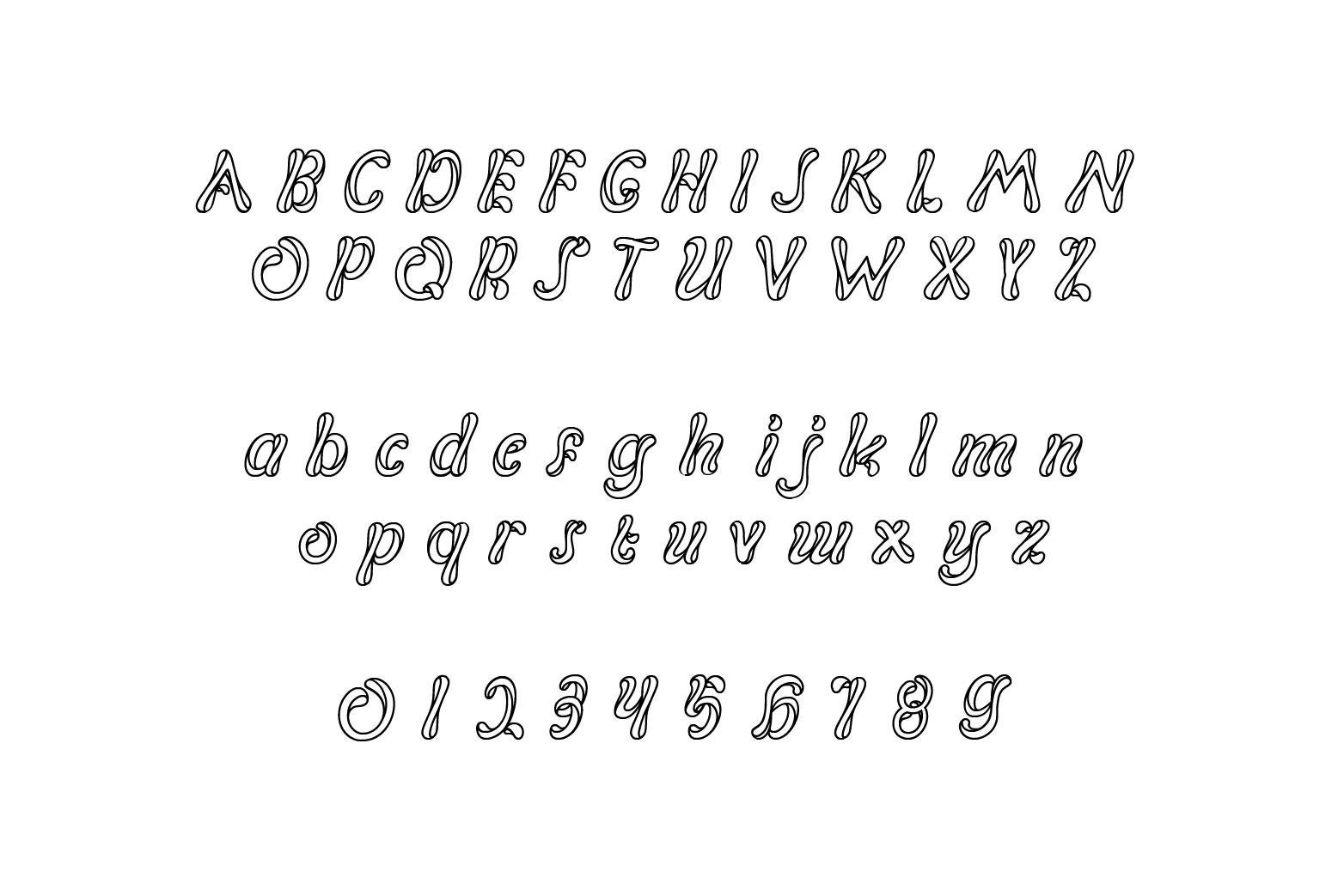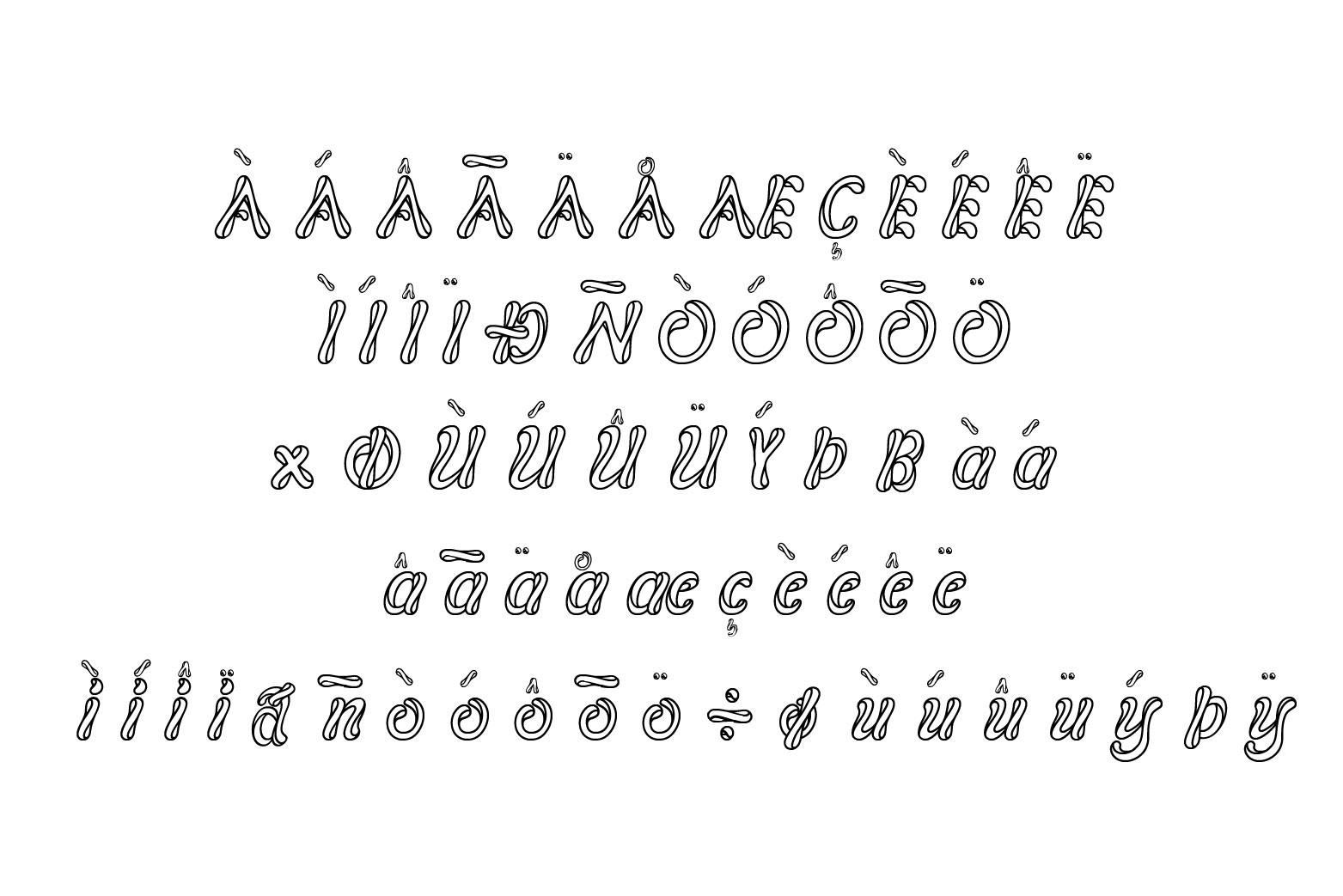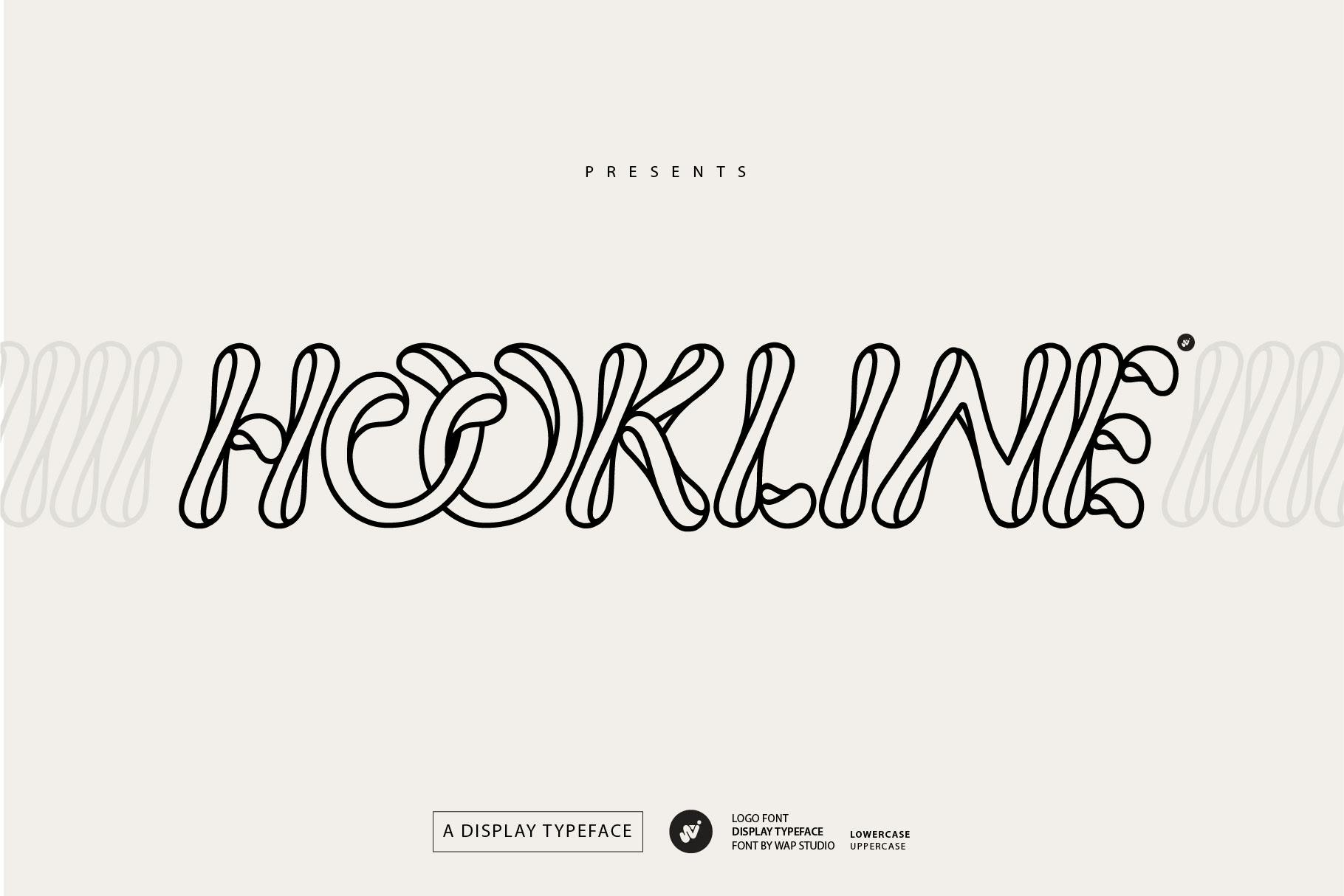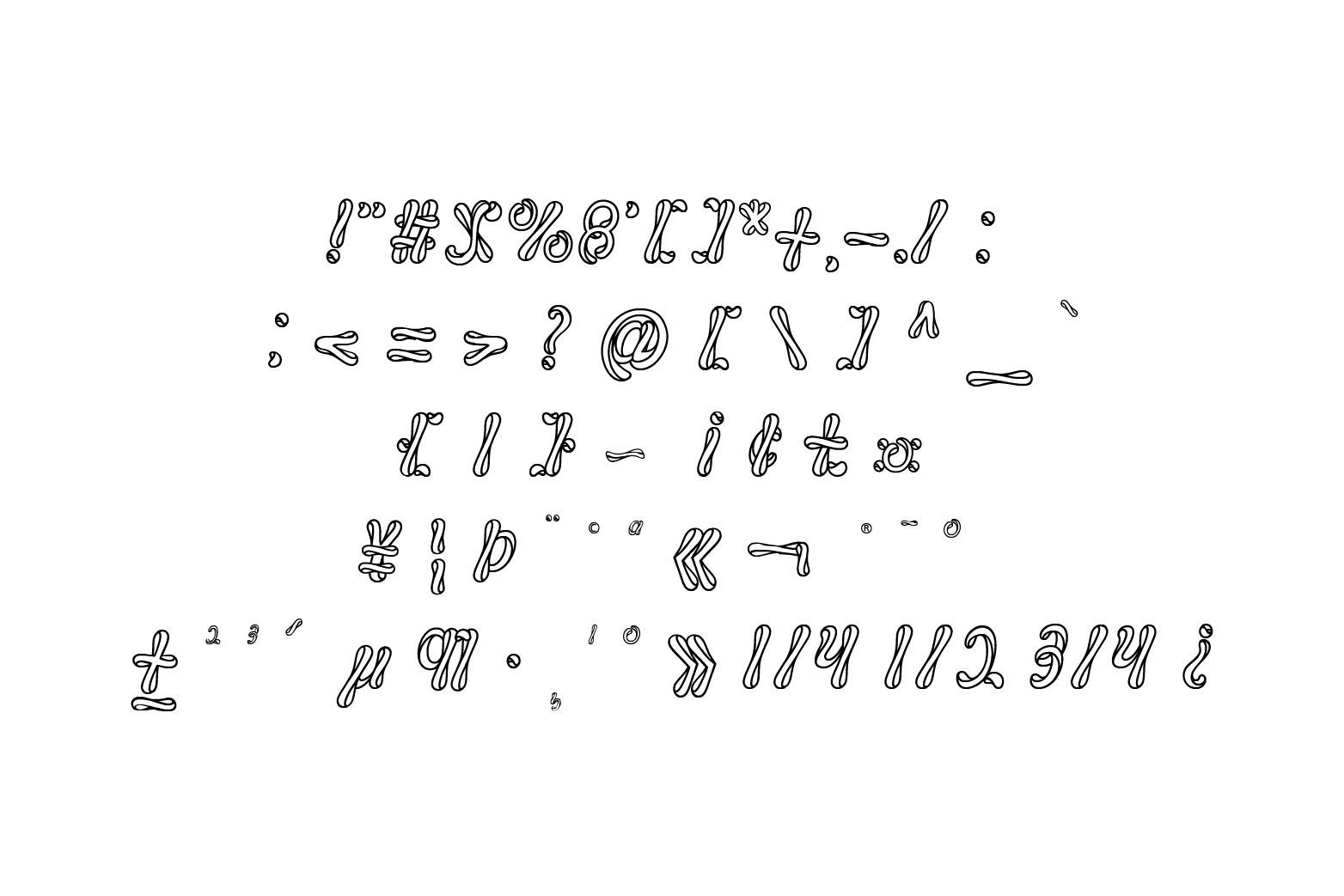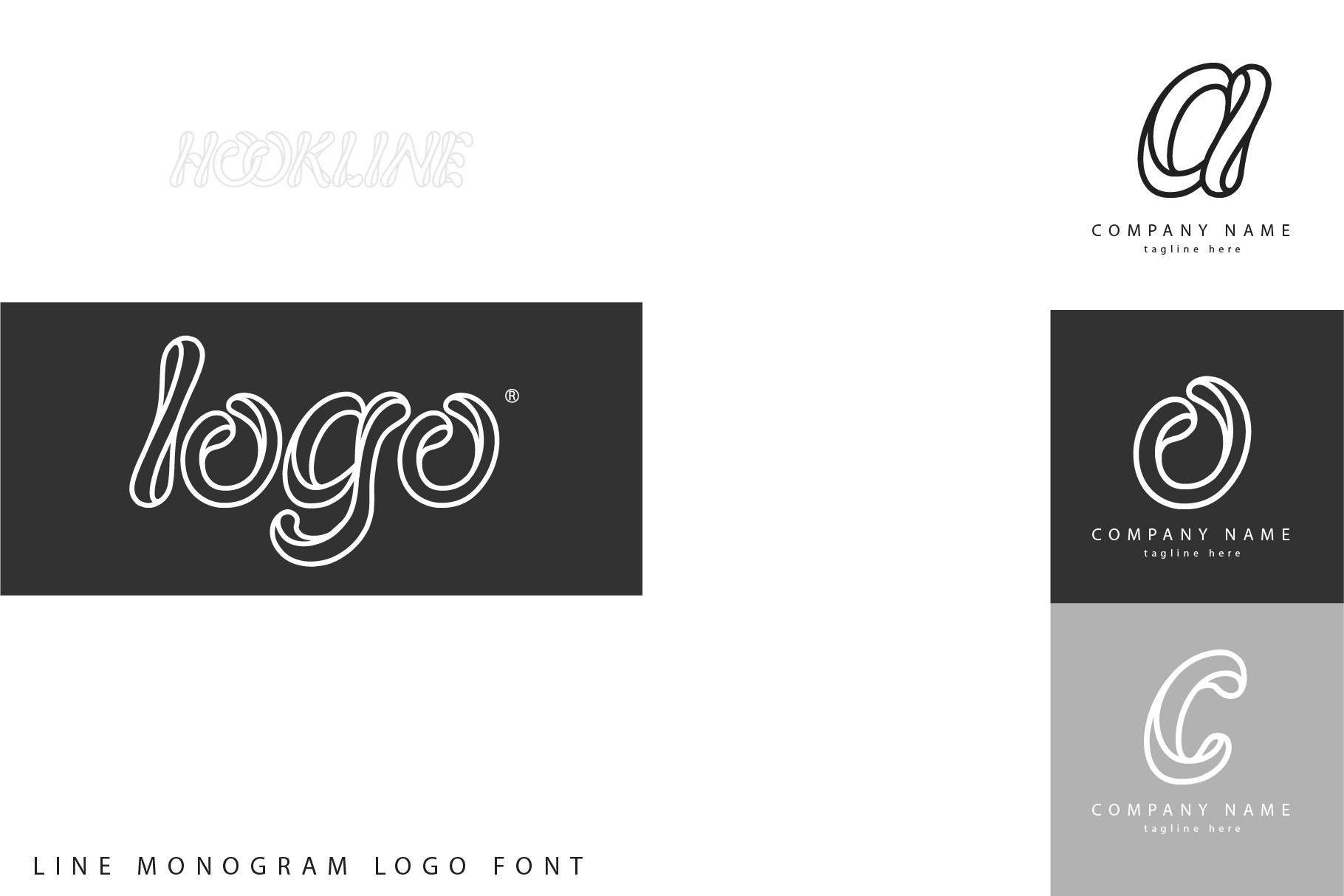
دانلود فونت HOOKLINE برای طراحی لوگو و برندینگ
HOOKLINE Monogram rounded logo font
فونت HOOKLINE، گزینه‌ای ایده‌آل برای طراحی‌های مختلف!
فونت HOOKLINE برای پروژه‌های متنوعی از جمله طراحی لوگو و برندینگ، عنوان‌ها، دعوت‌نامه‌ها، پوسترها، بروشورها، طراحی‌های عروسی، پست‌های شبکه‌های اجتماعی، تبلیغات، بسته‌بندی محصولات، طراحی محصولات، برچسب‌ها، عکاسی، واترمارک‌ها، رویدادهای ویژه و عناوین پوستر فوق‌العاده خواهد بود.
• مناسب برای طراحی لوگو و برندینگ
• قابل استفاده در پروژه‌های تبلیغاتی و اجتماعی
• ایده‌آل برای طراحی‌های عروسی و دعوت‌نامه‌ها